Deleatur
Das »Deleatur« ist eine suspensive Abbreviatur bzw. ein Abkürzungszeichen für »Soll gestrichen werden«; Deleaturzeichen; Tilgungszeichen. Das Deleatur ist ein Korrekturzeichen.
Etymologisch von lat. »deleatur« für »es möge beseitigt werden bzw. »es möge getilgt werden«. Ein Deleaturzeichen kennzeichnet in einem Layout, einem Manuskript, einem Typoskript, einer Satzfahne, einem PDF, einem Ausdruck, einem Proof oder einem Andruck Schriftzeichen, Wörter, Textpassagen oder Layoutelemente, die ersatzlos gestrichen werden sollen.
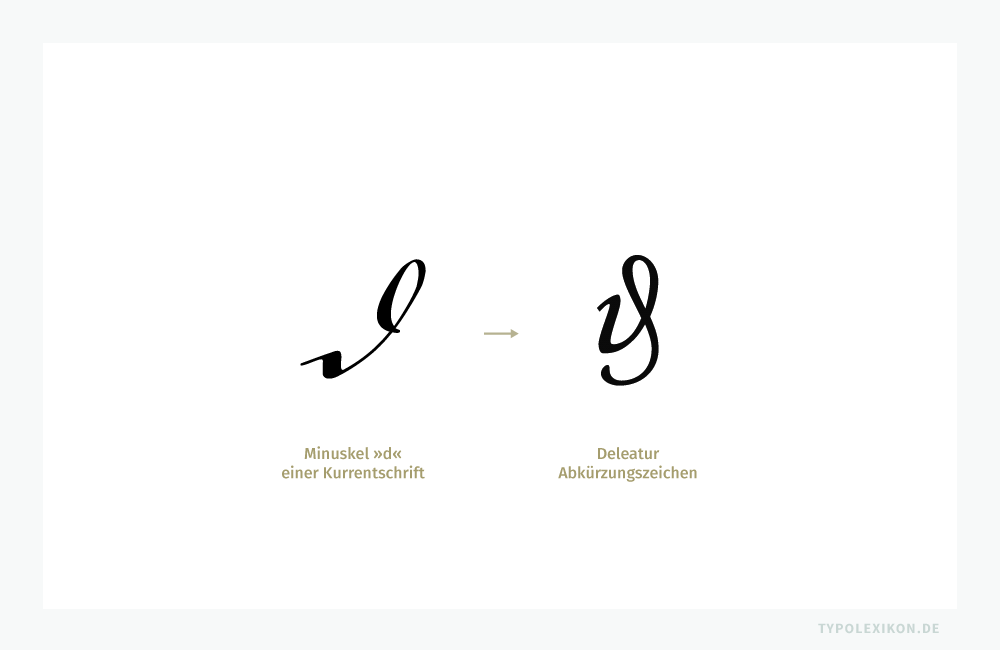
Das Deleaturzeichen (Tilgungszeichen) ist eine kalligrafische Abbreviatur, explizit ein Abkürzungszeichen, dass sich aus der Minuskel »d« der deutschen Kurrentschrift (Schreibschrift) entwickelt hat und das lat. Wort »deleatur« (das ist zu tilgen) abkürzt. Das Deleaturzeichen zählt zu den Korrekturzeichen.
Die Form des Tilgungszeichen geht auf den Kleinbuchstaben »d« in der deutschen Kurrentschrift zurück.